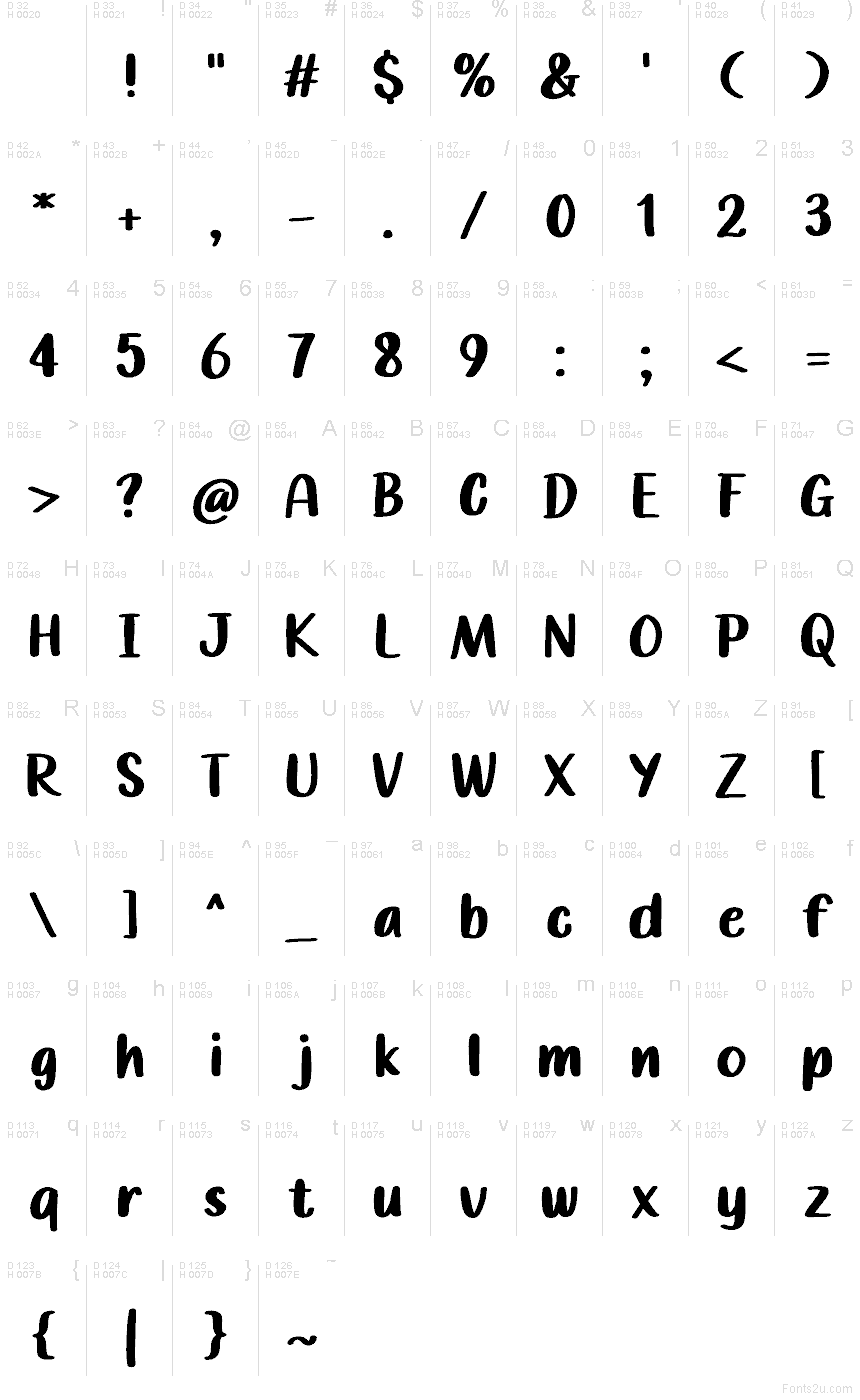
Banana Good
Banana Good від Hello God Studio — це безкоштовний рукописний шрифт із м’якими, заокругленими лініями та легким нахилом. Знаки виглядають невимушено та природно завдяки широким вигинам і відкритим формам, що робить накреслення легким, а не жорстким.
Banana Good чудово підходить для логотипів, пакування, коротких цитат, меню кафе, дописів у соцмережах та оригінальних запрошень. Цей безкоштовний шрифт додає проектам відчуття теплоти та індивідуальності, зберігаючи при цьому хорошу читабельність.